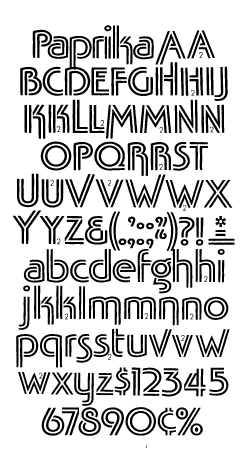
Meine Verwandten von der Turnerschaft Dornbirn fragen: "was haben wir für eine Schrift im Logo"?
Sebastian sagt: "muss ich mir das Logo nochmal ansehen, sollte aber kein Problem sein."
Und jetzt steh ich da ... :?
Ich sage jetzt mal das Logo ist 20 Jahre alt oder älter, also welche Schrift könnte es sein?
Mit der Dax gemein (wie im Titel suggeriert) hat sie natürlich nur die anstrichlosen "r" und "n", ansonsten ist es deutlich was anderes.
Spontan hat mich das an die Noa erinnert, aber die isses auch nicht … oder es wurde einges noch handgezupft.
Das wollte ich auch gerade fragen. Ich habe mal in meine alten Berthold-Layousatz-Headline-Fonts-Synopsen geschaut. Ohne Erfolg. Da findet man normalerweise fast alles. Okay, der Font sieht doch recht modern aus, ...
schwalbenkönig hat damals die ganzen berthold, mecanorma und typo-bach fotosatzkataloge abgesetzt und nun hat er ... naja, nicht-typografen würden sagen ... einen an der klatsche. ich finds toll! :cheer: danke für diesen super fund.